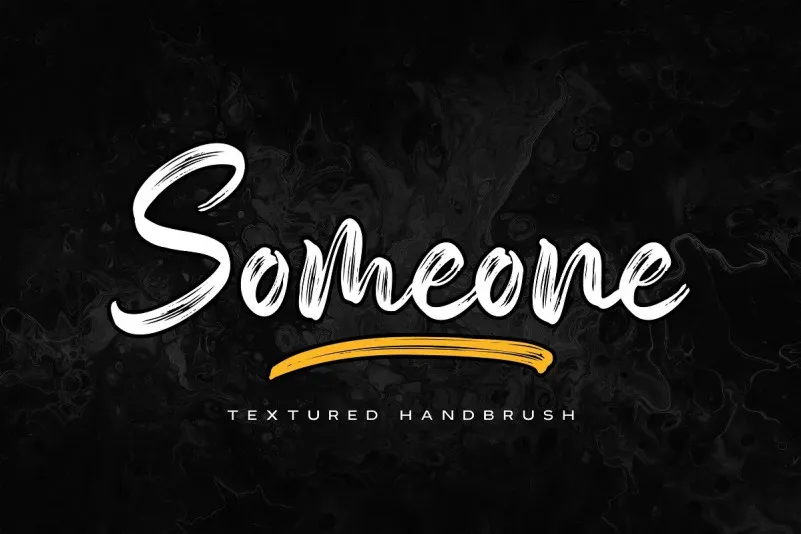
Esta é uma fonte escrita à mão relaxada e flutuante criada pela Almarkha Type, com letras afiadas e belas que criam fontes modernas, trendy e elegantes. Esta fonte é ótima para projetos criativos como marca d’água em fotografias, perfis de logotipo, design fotográfico, convites, anúncios, designs de produto, estaçãoaria, festas de casamento, etiquetas ou embalagens. Ela também se encaixa perfeitamente para eventos especiais ou qualquer coisa que precisa da textura do escritor à mão. Almarkha Type não inventou esses detalhes, mas o nome da font é ‘Someone Font’, uma sugestão original e envolvente para esta categoria de fontes script. Sem dúvidas, esta fonte trará um toque autêntico e criativo a qualquer projeto.